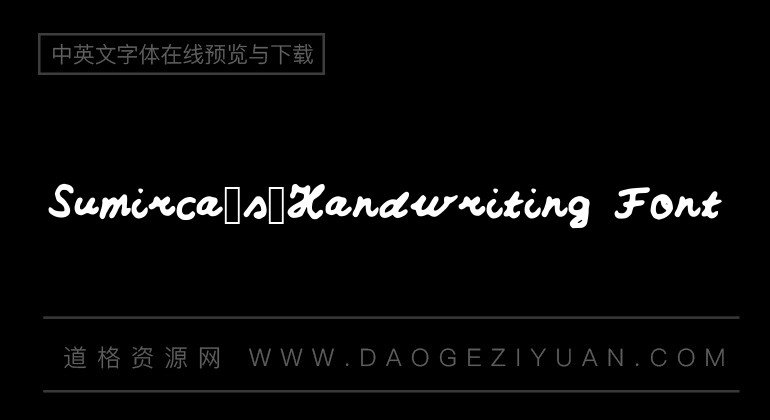
Sumirca_s_Handwriting Font 是一种手写风格的字体,它的设计灵感来自于人类书写的自然流畅性。这种字体的特点是具有非常自然的笔画和线条,使其看起来更像是人类手写的文字。 Sumirca_s_Handwriting Font 字体的大小适中,非常适合用于设计卡片、海报、传单等场合。它的风格轻快、活泼,非常适合用于表达轻松、愉快的情感。此外,这种字体还包含了多种不同的字母和符号,可以满足不同需求的设计师使用。 总之,Sumirca_s_Handwriting Font 是一种流畅、自然的手写风格字体,非常适合用于传达轻松、愉快的情感。内容介绍
Sumirca_s_Handwriting Font是一款非常不错的手写艺术字体,具有很好的视觉感,适合于文化类的宣传设计、商业类品牌的广告和产品包装设计以及个性化文字排版等较多场景。